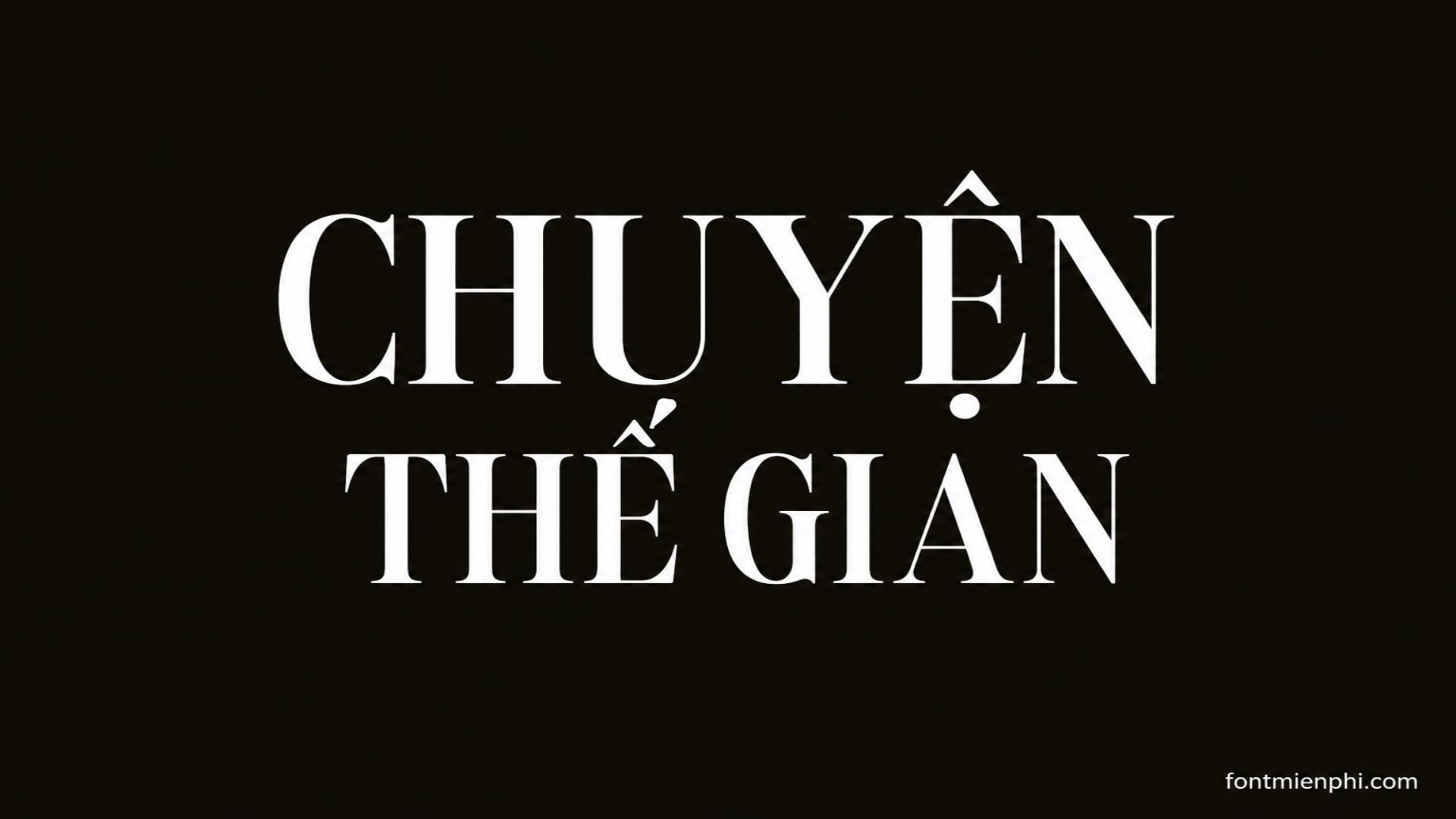
Tải Font Việt Hóa 1FTV VIP Neue Kentish Caps – Đỉnh Cao Phông Chữ In Hoa Sang Trọng
Nếu bạn đang tìm kiếm một phông chữ để khẳng định đẳng cấp, sự uy quyền và nét sang trọng tuyệt đối cho các dự án thiết kế, thì Font Việt hóa 1FTV VIP Neue Kentish Caps chính là “chân ái” mà bạn không thể bỏ qua. Nằm trong bộ sưu tập VIP đắt giá, phông chữ này mang đến một diện mạo đầy quyền lực nhưng không kém phần tinh tế, hoàn hảo cho các ấn phẩm mang tính biểu tượng.
1. Tổng quan về Font 1FTV VIP Neue Kentish Caps
1FTV VIP Neue Kentish Caps là một phông chữ được thiết kế chuyên biệt ở định dạng All-Caps (chỉ bao gồm chữ in hoa). Tiền tố “Neue” (mới) trong tên gọi ngầm khẳng định đây là sự làm mới, một bản nâng cấp mang hơi thở hiện đại dựa trên những đường nét cổ điển, chuẩn mực.
Sở hữu cấu trúc vững chãi, tỷ lệ hình học cân đối và các đường nét thanh đậm được xử lý vô cùng tinh xảo, Neue Kentish Caps toát lên vẻ đẹp của sự trưởng thành và chuyên nghiệp. Để giúp các nhà thiết kế Việt Nam khai thác tối đa sức mạnh của phông chữ này, đội ngũ 1FTV đã tiến hành Việt hóa vô cùng cẩn thận. Từng dấu thanh, dấu mũ đều được thiết kế lại để đồng nhất tuyệt đối với form dáng in hoa bề thế của chữ gốc, loại bỏ hoàn toàn tình trạng lệch dấu hay phá vỡ cấu trúc tổng thể.
2. Đặc điểm nổi bật của bản Neue Kentish Caps Việt hóa
Sự xuất hiện của 1FTV VIP Neue Kentish Caps trong kho tài nguyên của bạn sẽ giải quyết triệt để bài toán tìm kiếm phông chữ tiêu đề cao cấp, nhờ những ưu điểm vượt trội:
• Uy lực thị giác mạnh mẽ: Định dạng 100% in hoa giúp mọi thông điệp được viết ra đều mang sức nặng, thu hút sự chú ý ngay lập tức và thể hiện sự tự tin của thương hiệu.
• Tỷ lệ vàng trong thiết kế chữ: Các chữ cái có độ rộng và chiều cao được tính toán kỹ lưỡng, tạo nên một nhịp điệu đọc vô cùng hoàn hảo, sang trọng nhưng không bị phô trương.
• Kerning Tiếng Việt cực chuẩn: Khoảng cách giữa các chữ cái in hoa (đặc biệt là các chữ có dấu như Ắ, Ộ, Ễ…) được tinh chỉnh thủ công, mang lại một khối văn bản chắc chắn, không bị rời rạc.
• Chi tiết tinh tế: Dù là chữ in hoa mạnh mẽ, nhưng các góc cạnh và nét bo (nếu có) đều được làm mượt, hiển thị cực kỳ sắc nét trên các ấn phẩm in ấn khổ lớn.
3. Ứng dụng thực tế của 1FTV VIP Neue Kentish Caps
Là một phông chữ sinh ra để làm tiêu đề và biểu tượng, 1FTV VIP Neue Kentish Caps tỏa sáng rực rỡ nhất trong các dự án mang tính cao cấp:
Gợi ý phối Font (Typography Tip): Vì Neue Kentish Caps là font thuần in hoa, tuyệt đối không sử dụng nó cho các đoạn văn bản dài (Body text). Hãy để nó làm nhân vật chính ở các Tiêu đề (H1) hoặc Logo, và kết hợp cùng một phông chữ Serif hoặc Sans-serif mỏng, thanh lịch (như Playfair Display hoặc Montserrat) cho phần nội dung phụ để tạo sự cân bằng hoàn hảo.
• Thiết kế Logo & Monogram: Lựa chọn số 1 để làm logo cho các tập đoàn tài chính, khách sạn 5 sao, thương hiệu thời trang nam cao cấp, hoặc các hãng xe hơi sang trọng.
• Bao bì sản phẩm (Packaging): Nâng tầm đẳng cấp cho các thiết kế nhãn mác rượu vang, xì gà, cà phê thượng hạng hoặc nước hoa.
• Thiết kế Biên tập (Editorial Design): Dùng làm tiêu đề chính trên trang bìa các tạp chí doanh nhân, kiến trúc, phong cách sống.
• Poster Phim & Ấn phẩm truyền thông: Cực kỳ phù hợp với các bộ phim mang chủ đề hành động, lịch sử, trinh thám hoặc các sự kiện vinh danh hoành tráng.